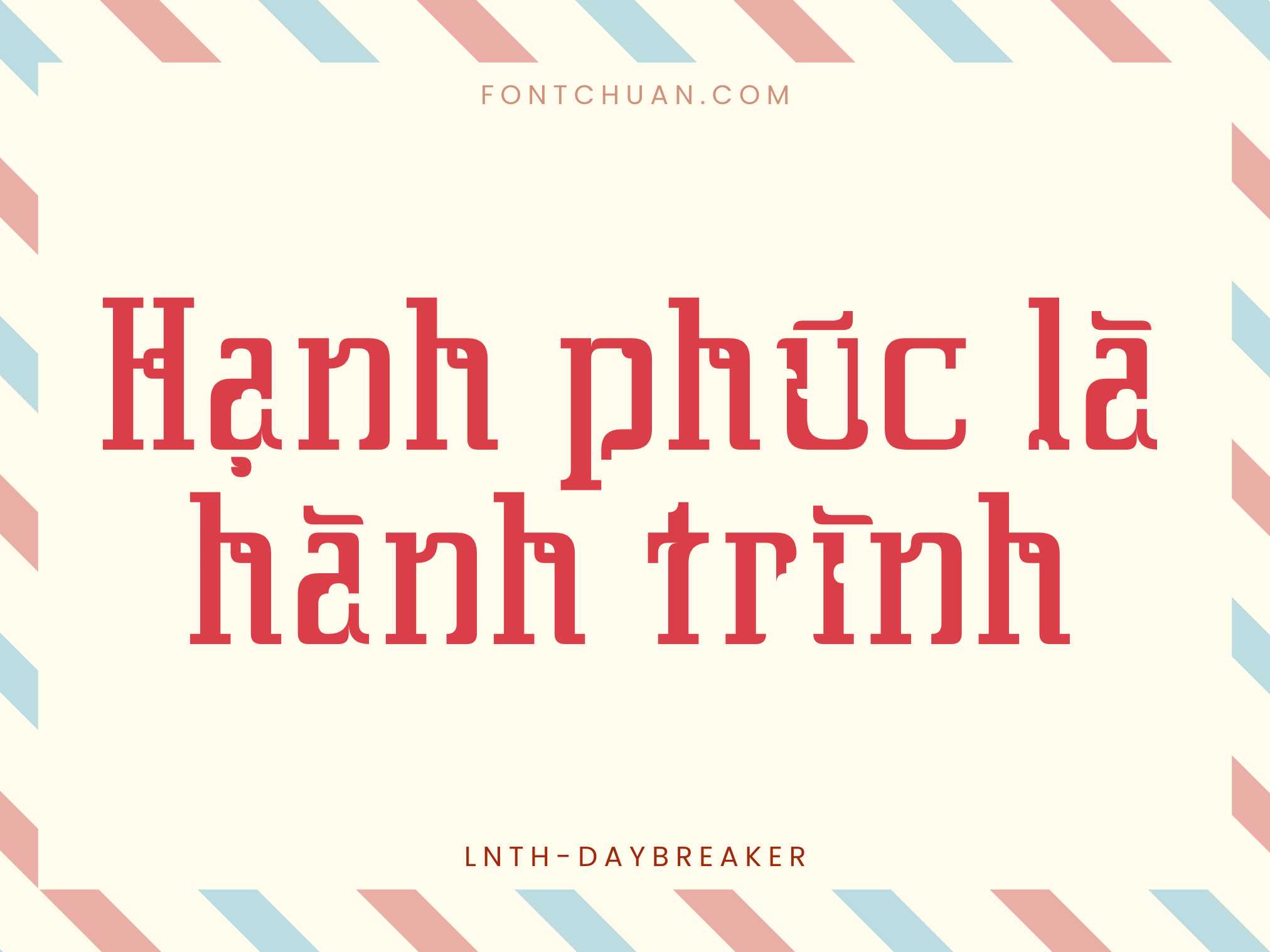
Font LNTH Daybreaker Việt Hóa
Daybreaker là một phông chữ được thiết kế bởi Darren Rigby, mang phong cách cổ điển và độc đáo, đồng thời chịu ảnh hưởng từ Font Gothic, với các đường nét sắc sảo và cấu trúc chữ mạnh mẽ. Phông chữ này tạo cảm giác truyền thống và nghệ thuật, phù hợp cho nhiều dự án thiết kế cần sự tinh tế và sáng tạo. Bản Việt hóa do LNTH thực hiện giúp Daybreaker hỗ trợ đầy đủ các ký tự tiếng Việt, giúp người dùng dễ dàng áp dụng trong các dự án đa ngôn ngữ. Phông chữ này đã được sưu tầm và đăng tải bởi thành viên của Font Chuẩn nhằm đáp ứng nhu cầu đa dạng của cộng đồng thiết kế.
Về đặc điểm thiết kế, Daybreaker sở hữu các ký tự được thiết kế tỉ mỉ, mang lại cảm giác cổ điển và tinh tế. Phông chữ này đặc biệt phù hợp cho các dự án như thiệp mời, bìa sách, poster, logo và các ấn phẩm quảng cáo, nơi cần sự trang nhã và ấn tượng mạnh mẽ. Ngoài ra, Daybreaker cũng thích hợp cho các sự kiện như lễ hội, sinh nhật, Valentine và Trung thu, mang lại không khí ấm áp và lãng mạn. Trong lĩnh vực ngành nghề, phông chữ này được ứng dụng rộng rãi trong quảng cáo, thiết kế thiệp cưới, giáo dục và công nghệ, góp phần tạo nên sự độc đáo và thu hút cho các sản phẩm và thương hiệu.